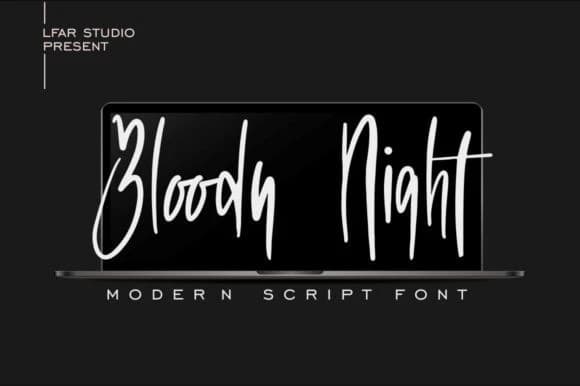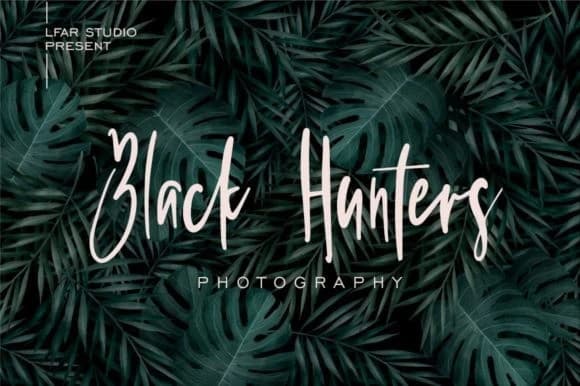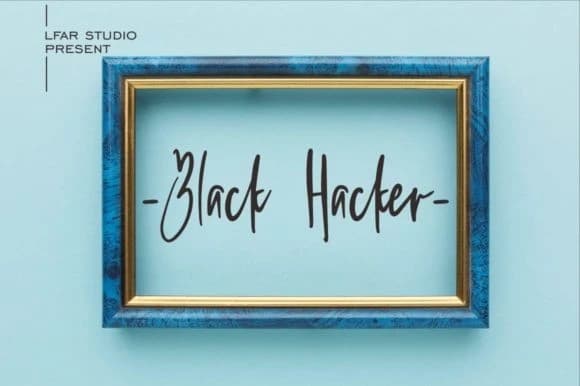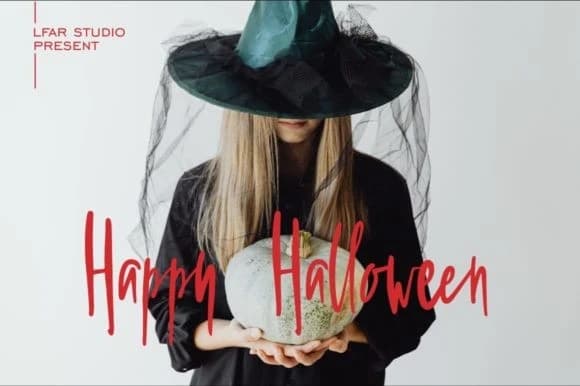
Bloody Night Font
Bloody Night Font, korku hissi veren karanlık görünümlü bir el yazısı fontudur ve korkutucu bir izlenim yaratır. Birçok film başlığı, kitap kapakları, Cadılar Bayramı mesajları ve çok daha fazlasında çarpıcı görünür.
Bloody Night Font korku hissi uyandıran ve korkutucu bir etki bırakan karanlık görünümlü bir el yazısı fontudur. Farklı film başlıklarında, kitap kapaklarında, Cadılar Bayramı tebriklerinde ve çok daha fazlasında muhteşem görünüyor.